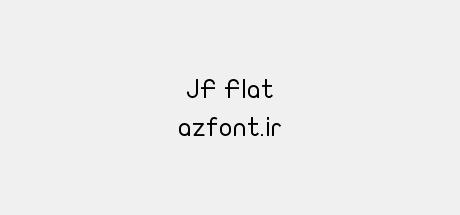
JF Flat
فونت زیبای رایگان JF Flat
قلم زیبای JF Flat Regular از سری قلم های بسیار زیبا برای تایپوگرافی و لوگو تایپ می باشد.این قلم در وزن Regular و توسط Font@zakdesign.net طراحی و منتشر شده است.
Ahmed Abd El Halim
Flat Font - Arabic & Latin Typeface.